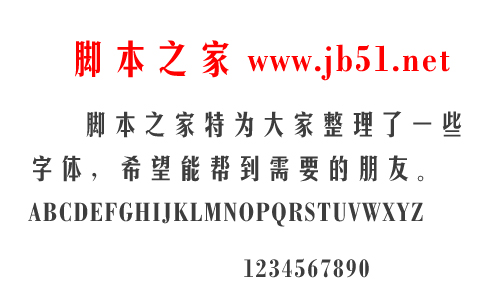
碳纖維長(zhǎng)美黑簡(jiǎn)體字體是碳纖維字庫(kù)中的一款長(zhǎng)美黑字體,非常漂亮且精致,適應(yīng)于各種活動(dòng)、廣告牌等等領(lǐng)域使用,歡迎喜歡碳纖維長(zhǎng)美黑簡(jiǎn)體的朋友前來下載使用。
碳纖維長(zhǎng)美黑簡(jiǎn)體